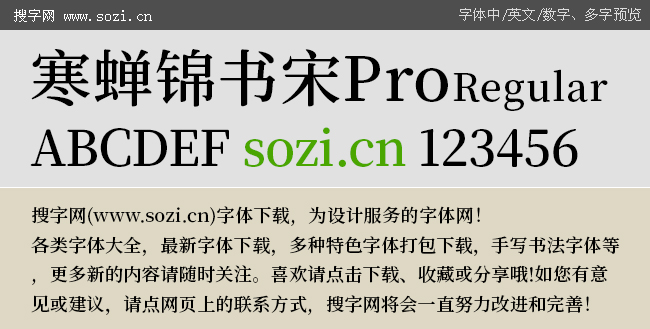
寒蟬錦書宋Pro_Regular
搜字網給大家提供一款寒蟬錦書宋Pro_Regular中文字體下載,寒蟬錦書宋是基于思源宋體進行修改的一款字體,在思源宋的基礎上添加圓角,變成更加溫潤的宋體,排版細節優化,重構字重比例,使字體粗細更加均衡,便于閱讀,包含12種字重文件,適用于標題設計、海報設計、書籍排版以及網頁設計等應用。